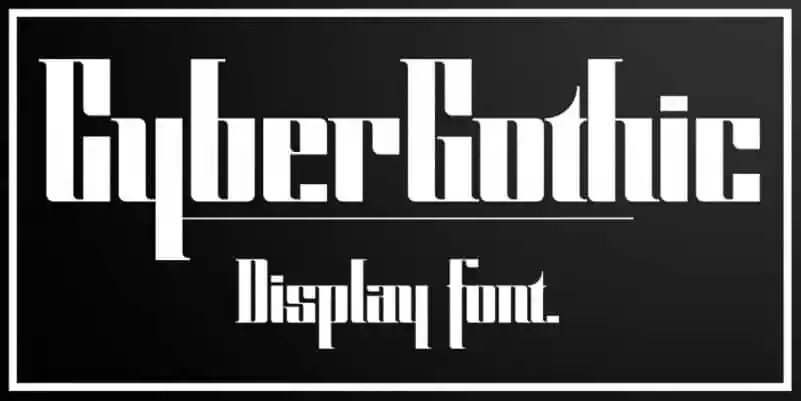
A Cyber Gothic Display Font é uma nova tipografia modelada em blocos que destaca as serifas inclinadas em ângulo consistente. Esta elegante escolha se torna ainda mais atraente graças à agressividade da tipografia, onde o ritmo brutal de linhas pesadas e serifas finas é combinado com espaçamento entre letras estreito. A fonte AZetype criou uma experiência visual impactante para aplicação em materiais de design digital e impressão. Com Cyber Gothic Display Font, você pode transformar qualquer página em um elemento central do seu projeto, destacando-se da multidão com seu estilo único e eficaz.